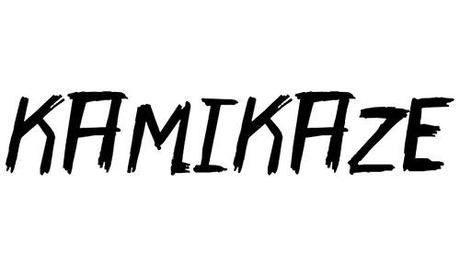
Come detto piu’ volte il font scelto puo’ influenzare positivamente gli utenti di un sito web, aggiungere un valore estetico alle pagine web e aumentare il numero di lettori e la potenza del nostro messaggio che vogliamo trasmettere. Insomma, una forte comunicazione e dei contenuti importanti, necessitano di un font elegante, grintoso e inerente. I font possono determinare il successo o il fallimento di un sito web. In questo articolo ho raccolto dei bellissimi caratteri a pennello che potete utilizzare nel vostro design per renderlo ancora piu’ accattivante e originale. Font Brush possono far apparire un messaggio piu’ vivace, elegante e molto cool; rilassante, informale e molto funky. I font brush sono indicati per progetti di logo design, presentazioni efficaci e titoli molto audaci. Date uno sguardo alla mia raccolta di eleganti caratteri pennello e scegliete quello che piu’ si confa’ al vostro stile. Buona scelta e buon download!
XALIGRAPHY
font pennello
KAMIKAZE
font pennello
ONE DIRECTION
font pennelloSHORTBRUSH
font pennello
ANN BRUSH
font pennello
DARE
font pennello
THE LOW DOWN
font pennello
QUINQUENNIAL
font pennello
KILLER INSTINCT
font pennello
LALOUZZ
font pennello
QUAST
font pennello
MIDNIGHT
font pennello
WIZARD TAINT
font pennello
MESSY BRUSH
font pennello
GRAND DUCHESS
font pennello
IGNITE
font pennello
HILLWILLIAM
font pennello
FACE YOUR
font pennello